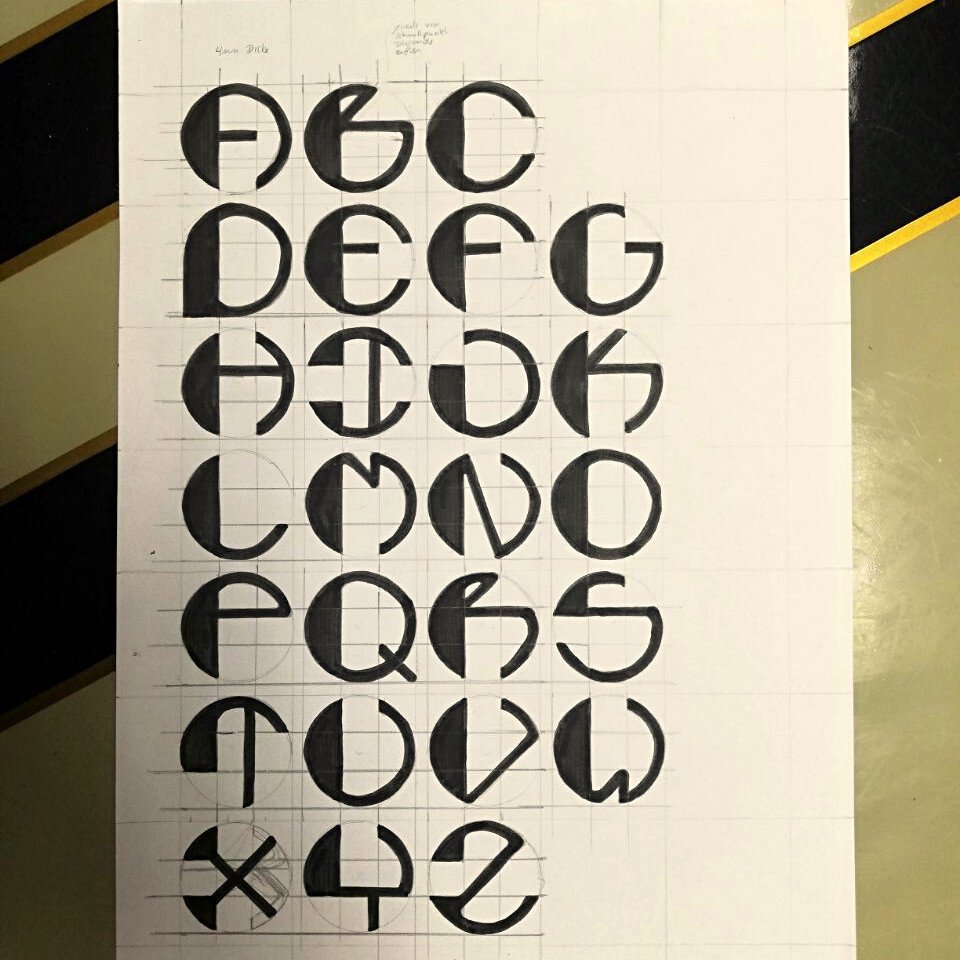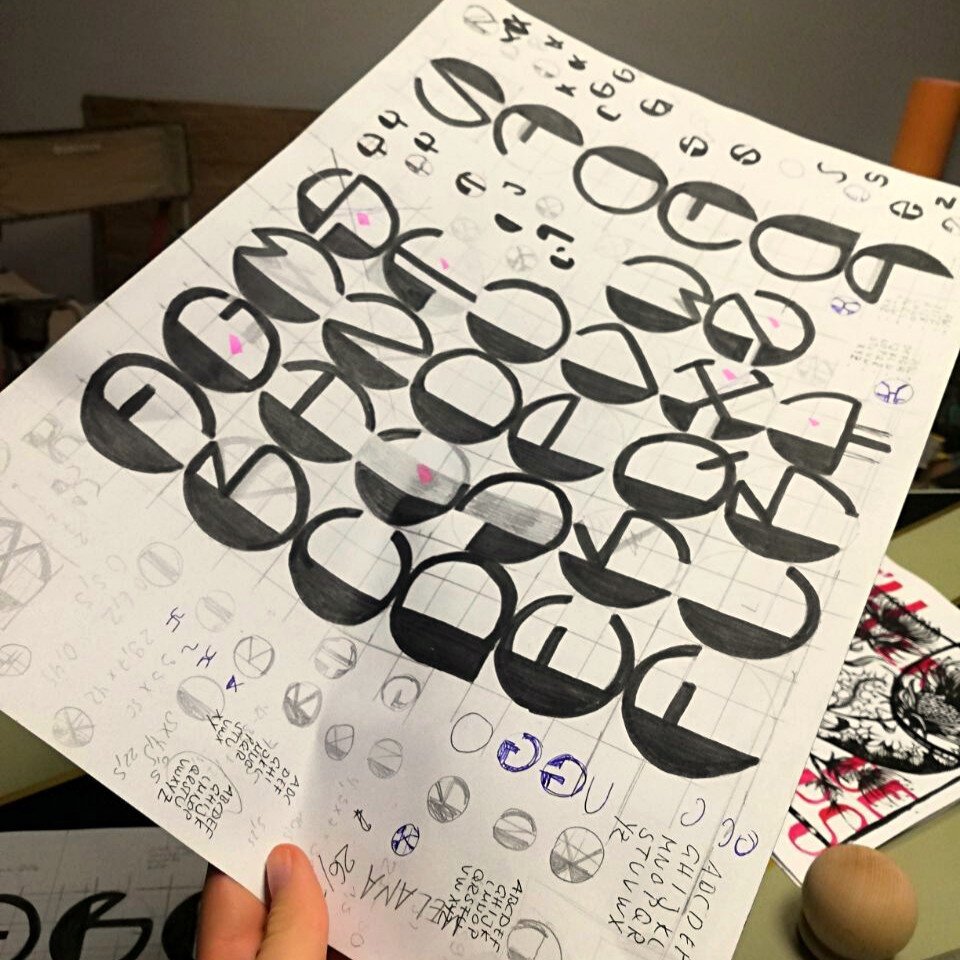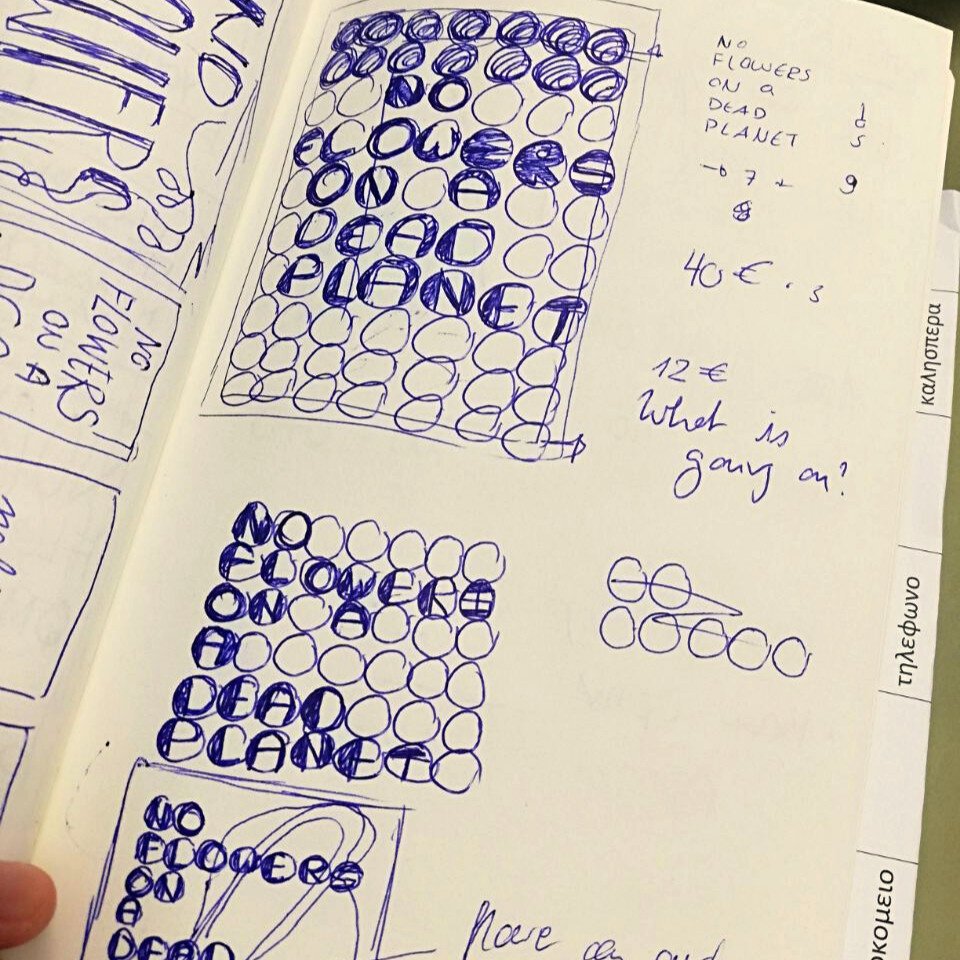
#Schriftarten
I wanted to create some nice lettering for a #linocut idea I have, but I could stop myself from developing the whole #font 😬 It was super fun, but with some letters I am not super happy yet, let's see where this goes ✨😁
What do you think? 🍃
- Sans-Serif-Schriften: Wirken modern und minimalistisch
- Schreibschriften: Eignen sich für kreative und individuelle Designs
- Display-Schriften: Auffällige Schriften für Überschriften
- Handgeschriebene Schriften: Vermitteln Persönlichkeit und Einzigartigkeit
Mit Schriftarten.io kannst du:
- Einfach die gewünschte Schriftart finden: Nutze die praktische Suchfunktion und Filter, um die Auswahl einzugrenzen.
- Die Schriftart in der Vorschau ansehen: Bevor du dich entscheidest, kannst du sehen, wie dein Text in der jeweiligen Schriftart aussieht.
- Die Schriftart mit einem Klick kopieren: Mühelos in dein Design-Programm einfügen.
Besonders praktisch für Einsteiger:
- Keine Anmeldung erforderlich: Du kannst Schriftarten.io direkt nutzen, ohne dich registrieren zu müssen.
- Kostenlos und legal: Viele Schriftarten können auch für kommerzielle Zwecke kostenlos verwendet werden.
Gestalte deine Projekte jetzt noch ansprechender und professioneller mit Schriftarten.io! Besuche die Webseite und entdecke die Vielfalt an kostenlosen Schriftarten.
Lebenslauf-Akte eines Flugzeugs als Ordner mit Registersortierung komplett in Comic Sans.
LibreOffice-Serie: Kompatible Schriftarten
Mit metrisch kompatiblen Schriftarten kann man in LireOffice Microsoft-Fonts ersetzen.
Wusstest du, dass Google Fonts allein über 1.000 Schriftarten führt?
Usability: Mit der passenden Schriftart 30 Prozent schneller lesen
Stimmt nicht, dass die #Microsoft-Schriftart #Segoe UI identisch ist mit Frutiger Next.
Die meisten Buchstaben, a-z, ja, abgesehen von eckigen (Frutiger) vs. runden (Segoe) Punkten.
Aber ß,$,&, @ sind in Segoe deutlich anders als in Frutiger. Und mMn deutlich hässlicher.